Font chữ đẹp để làm logo khách sạn - Gợi ý thiết kế chuẩn
Khi bắt đầu hành trình xây dựng hình ảnh thương hiệu cho khách sạn, logo chính là lời chào đầu tiên. Đây là biểu tượng nhận dạng, thông qua đó thương hiệu của bạn sẽ được nhận diện tốt hơn. Vì vậy, chọn font chữ đẹp để làm logo khách sạn luôn là bước đi quan trọng để gửi gắm tinh thần thương hiệu qua từng đường nét.
Gợi ý những font chữ đẹp để làm logo khách sạn
Mỗi khách sạn sẽ có phong cách, tên gọi khác nhau nên sẽ có những đặc điểm riêng để tạo được logo riêng. Việc lựa chọn bộ font đẹp, phù hợp sẽ giúp đánh thức cá tính ấy trong từng nét chữ. Dưới đây là một số font chữ đẹp để làm logo khách sạn Sao Thái Bình muốn gợi ý cho bạn để có thể thử sử dụng nhé!
Font Serif sang trọng
Đây là font chữ đẹp, phù hợp khách sạn cao cấp, phong cách châu Âu, hoài cổ. Một số font khác có tính chất rất phù hợp có thể sử dụng là:
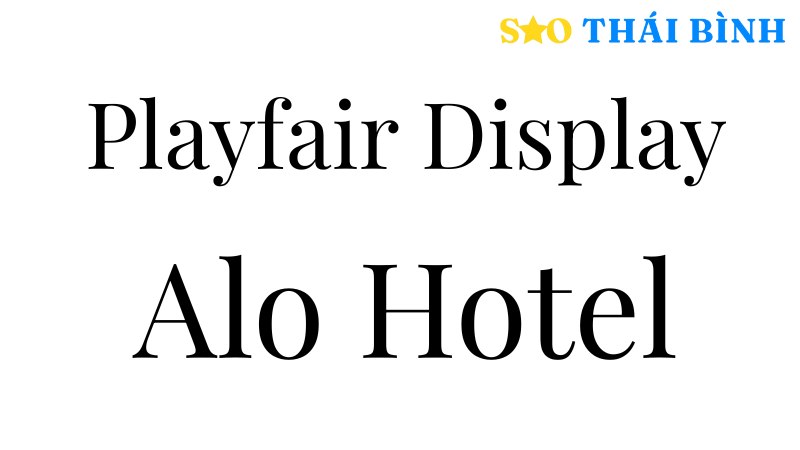
Gợi ý những font chữ đẹp để làm logo khách sạn - Playfair Display
- Baskerville
- Didot
- Playfair Display
- Cormorant Garamond
Font Sans-Serif hiện đại, tối giản
Hợp với khách sạn trẻ trung, tinh gọn, phong cách urban - Một số font khác có tính chất rất phù hợp có thể sử dụng là:
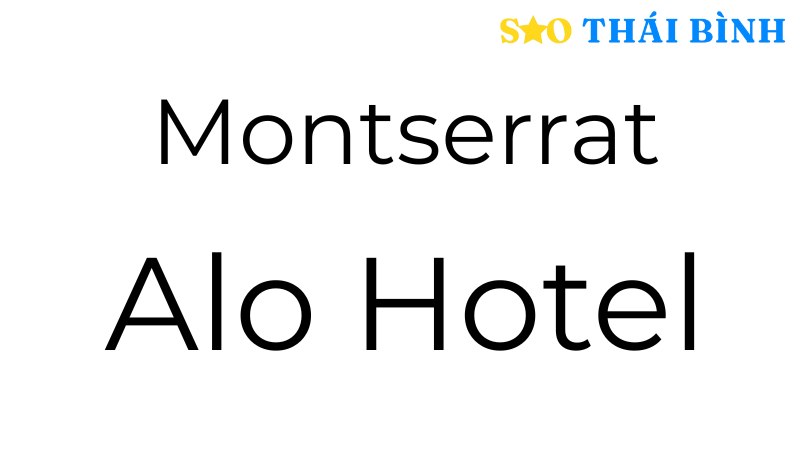
Font Montserrat hiện đại, tối giản cho logo khách sạn
- Montserrat
- Futura
- Helvetica Neue
- Lato
Font Signature - Calligraphy mềm mại
Lý tưởng cho resort, boutique hotel, mô hình nghỉ dưỡng - Một số font khác có tính chất rất phù hợp có thể sử dụng là:
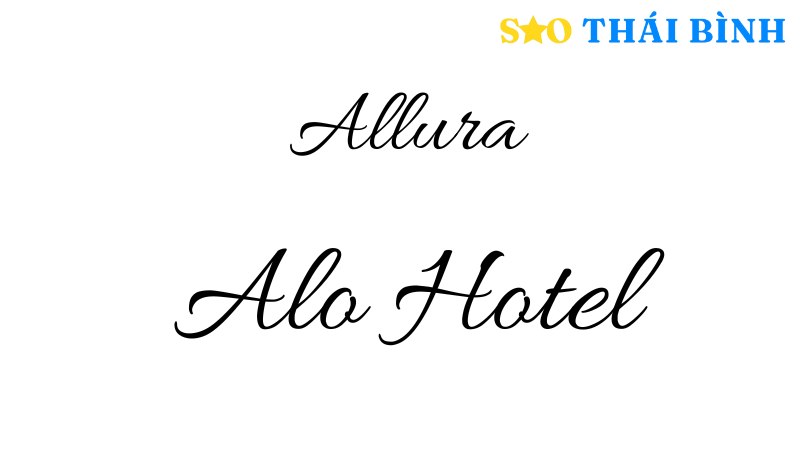
Font Allura mềm mại cho boutique hotel
- Great Vibes
- Allura
- Parisienne
Font Display độc bản - mạnh mẽ - kiến trúc
Rất hợp khách sạn doanh nhân hoặc khách sạn định hướng thiết kế - Một số font khác có tính chất rất phù hợp có thể sử dụng là:
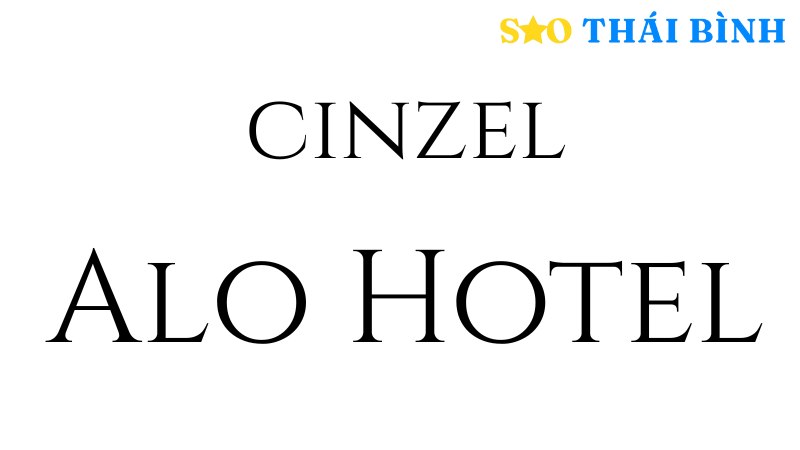
Font Cinzel độc bản - mạnh mẽ - kiến trúc
- Cinzel
- Trajan Pro
Từ khóa “font chữ đẹp để làm logo khách sạn” trên Google sẽ gợi ý cho bạn khá nhiều font khác nhau. Do đó, bạn nên xác định rõ phong cách muốn theo đuổi là gì, những nét đặc trưng cho khách sạn là gì rồi lựa chọn font chữ chính hoặc kết hợp nhiều font khác nhau để tạo nên “nhịp điệu chuẩn” cho thương hiệu của mình nhé!
Khi kết hợp cùng font chữ đẹp để làm logo khách sạn, các biểu tượng này tạo ra diện mạo nhất quán và giàu ý nghĩa.
Không có một công thức chung cho tất cả các kiểu logo hay áp dụng cho các khách sạn khác nhau. Mỗi dòng khách sạn là một câu chuyện riêng và tùy theo phân khúc mà phong cách thiết kế logo cũng sẽ có những điểm khác biệt.
Khách sạn nhà nghỉ (2-3 sao)
Nên chọn font sans-serif đơn giản, dễ đọc, màu sắc nhã nhặn như xanh - trắng - vàng nhạt. Logo nên tập trung vào sự thân thiện, dễ gần và ưu tiên thể hiện đầy đủ tên trên logo của mình.
Khách sạn vùng núi
Chọn font serif hoặc display hơi thô mộc, kết hợp màu nâu - xanh rừng - be. Biểu tượng: đỉnh núi, lá thông, mái nhà gỗ là cực kỳ phù hợp.
Khách sạn vùng biển
Ưu tiên font mềm mại, thoáng đãng như script mảnh hoặc sans-serif bo tròn. Cùng với đó là màu xanh biển, xanh pastel, trắng ngọc trai,... kết hợp với biểu tượng sóng biển, san hô, cánh chim, vỏ sò.
Khách sạn dành cho khách doanh nhân
Vì đây là tệp khách hàng cao cấp, những yêu cầu của họ khá cao, nên logo sang trọng có thể gây ấn tượng và tăng tỷ lệ lựa chọn của họ. Nên chọn font sans-serif vuông vắn, hiện đại, mạnh mẽ. Màu navy - đen - bạc - vàng gold kết hợp với biểu tượng mang tính hình học hoặc đường nét kiến trúc.
Khách sạn nghỉ dưỡng
Nên chọn font serif mềm hoặc signature tinh tế và kết hợp với màu be - kem - xanh olive. Ưu tiên những biểu tượng mang hơi hướng thiên nhiên, thư giãn như: lá, nước, ánh mặt trời mang cảm giác thư thái.